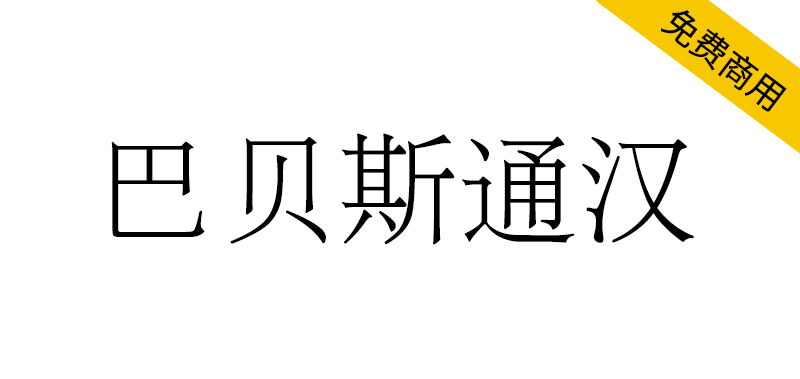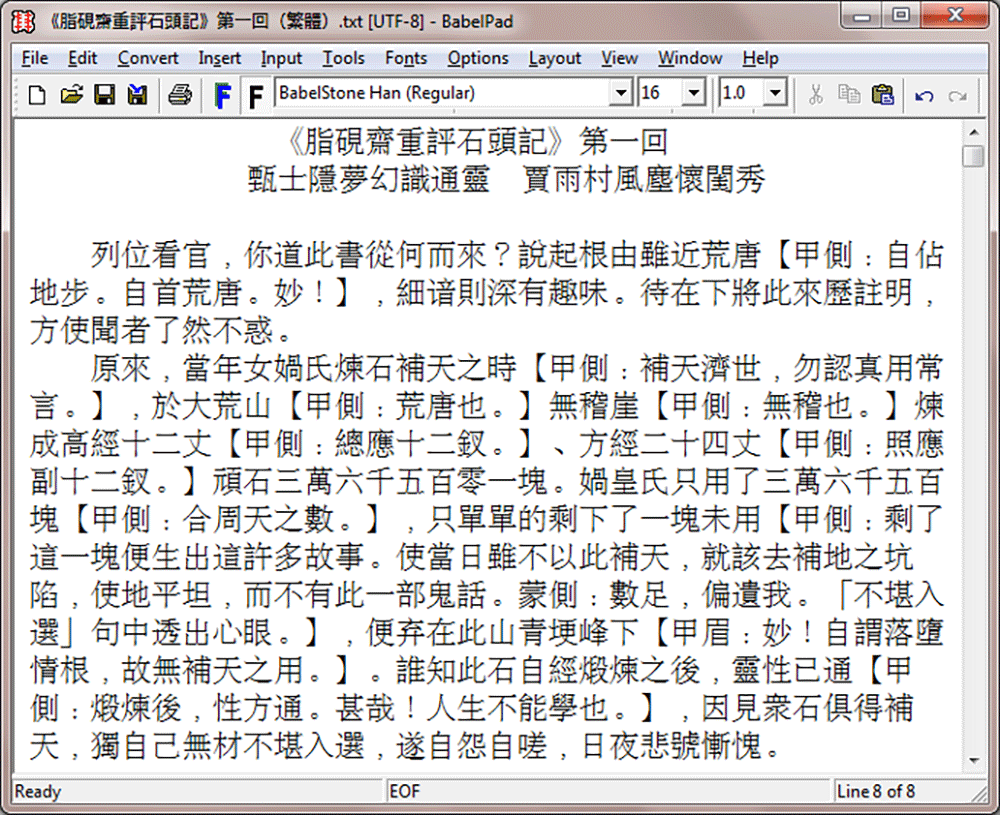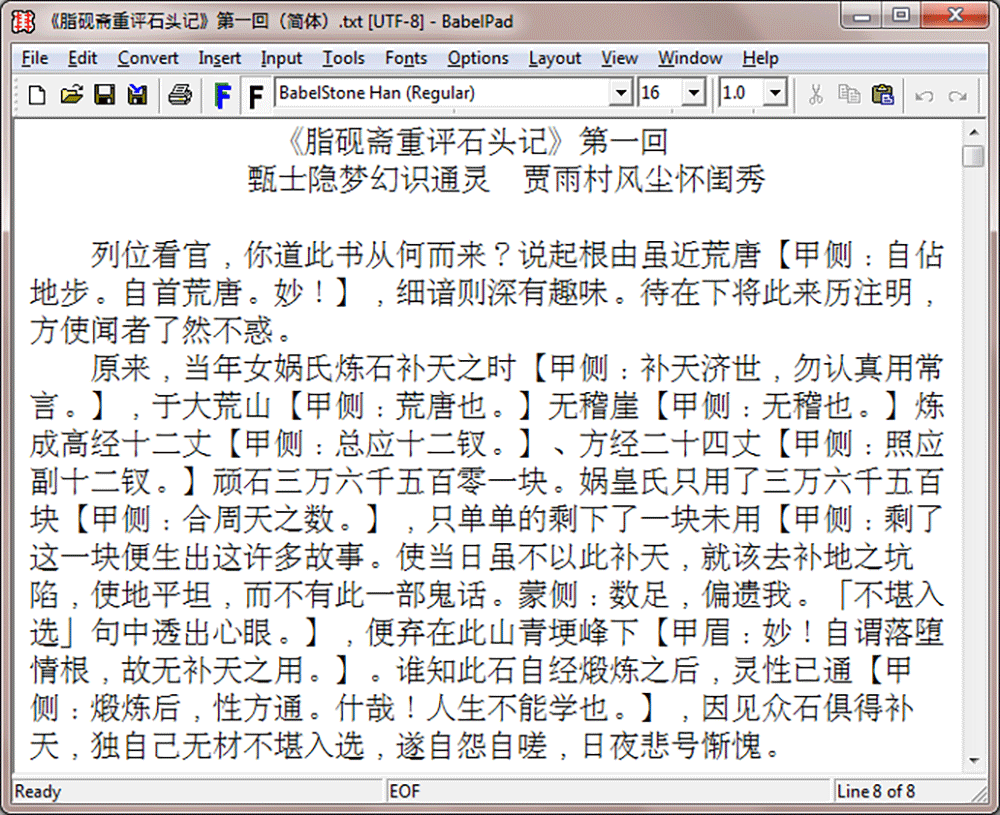
巴贝斯通汉(BabelStone Han)是一款免费Unicode中日韩统一表意文字字体,包含60,000余个汉字(含中文简体繁体、日文汉字、韩文汉字)及总计64,789个Unicode字符。该字体采用宋体/明体风格,字形以中国官方规范字形为基准,主要适用于现代标准汉语、文言文及多种汉语方言的书写,同时囊括大量日文、韩文、越南喃字和方块壮字专用字符。针对中文使用者,本字体完整覆盖Unicode收录的所有简体字及对应繁体字,并包含多数中日韩字体未收录的生僻字、古文字,以及甲骨文、金文、简牍、帛书等早期汉语文献学术转写专用字符。
本字体基于文鼎科技2001年发布的文鼎PL细上海宋(AR PL Mingti2L Big5)(13,068个表意文字)与文鼎PL简报宋(AR PL SungtiL GB)(6,763个表意文字)两款字体合并开发(原字体采用文鼎公共许可证授权)。经Unicode编码转换后的合并字体初始包含14,907个表意文字,现已扩展实现基础CJK区块(URO)、扩展A区、D区及I区的全字符覆盖,并对扩展B区、C区、E区、F区、G区、H区实现部分覆盖。原始CJK字形已参照Unicode码表G源字形进行标准化修正。
BabelStone Han v. 16.0.3 is a free Unicode CJK font with over 60,000 Han characters (hanzi, kanji, hanja), and 64,789 Unicode characters in total. It is a Song/Ming style (宋体/明體) font, with glyphs modelled on the official character forms used in the People's Republic of China, and is primarily intended for writing Modern Standard Chinese, Classical Chinese, and various Sinitic languages and dialects. However, it also includes a large number of characters used for Japanese, Korean, Vietnamese (Chữ Nôm), and Zhuang (Sawndip). For Chinese it covers both traditional form characters and simplified form characters (it has full coverage of all Chinese simplified characters included in Unicode, as well as all corresponding traditional form characters). The font also includes many rare or archaic characters that are not found in most CJK fonts, as well as many characters used for the scholarly transcription of Early Chinese texts written on bone, bronze, wood, bamboo, and silk.